"왜 다른 쇼핑몰은 세련되어 보이는데, 내 쇼핑몰은 묘하게 아마추어 같을까?"
뷰티, 의류, 리빙 카테고리의 스마트스토어를 운영하는 초보 셀러라면 한 번쯤 해봤을 고민입니다. 이 카테고리들의 공통점은 이성적인 설명보다 제품이 주는 '감성적 분위기'가 소비자의 지갑을 열게 만든다는 것입니다. 그리고 그 감성의 한 끗 차이를 결정하는 핵심 요소가 바로 '폰트(Font)'입니다. 비싼 디자이너를 고용하지 않아도, 트렌디한 글꼴 하나만 잘 쓰면 대기업 브랜드 몰 못지않은 감각적인 무드를 연출할 수 있습니다.
본 글에서는 "스마트스토어 상세페이지나 썸네일을 직접 만들 때 저작권 문제없는 상업용 무료 폰트 추천해 주세요. 가독성 좋고 트렌디한 느낌을 주는 폰트가 무엇인가요?"라는 셀러분들의 질문에 답하고자 합니다. 저작권 걱정 없이 안전하게 사용할 수 있으면서도, 브랜드의 가치를 높여줄 상업용 무료 폰트 추천 7종을 엄선하여 소개해 드립니다. 가독성과 감성을 모두 잡은 폰트 리스트를 통해 성공적인 스마트스토어 상세페이지 제작의 뼈대를 세우고, 여러분의 스토어 디자인 퀄리티를 한 단계 업그레이드해 보세요!
1. 독보적인 가독성, 현대적인 감성의 본문용 끝판왕 ‘프리텐다드(Pretendard)’
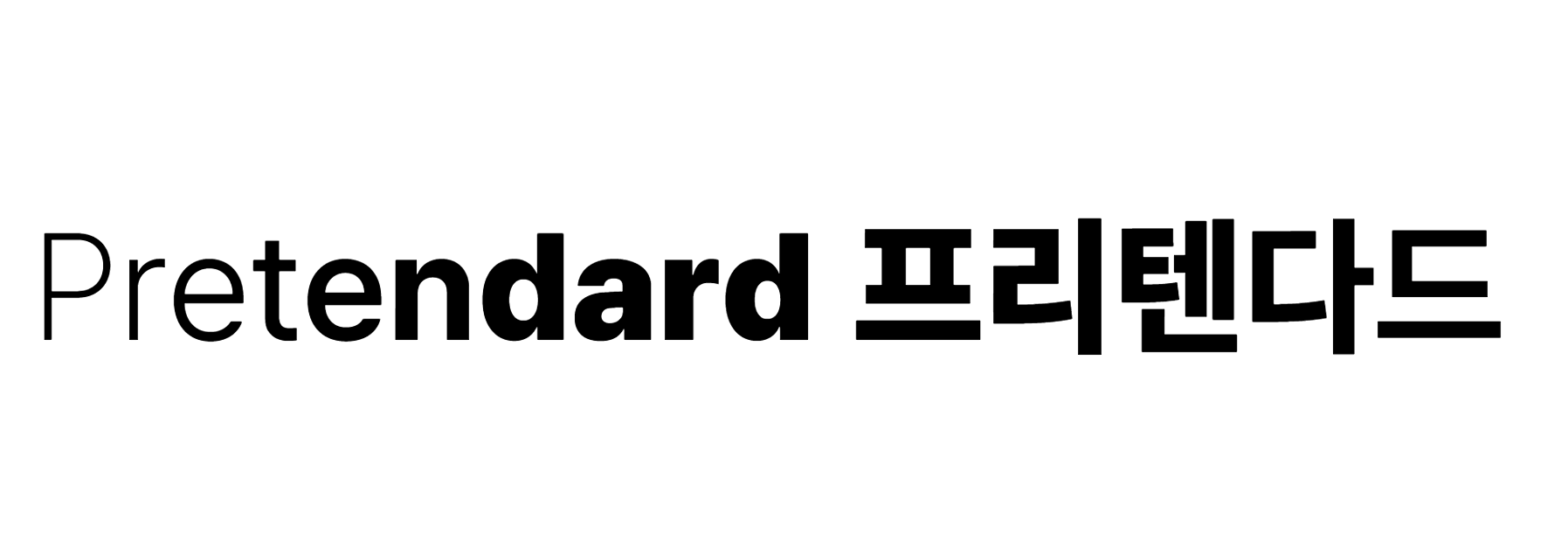
프리텐다드 특징 및 추천 카테고리 (의류/뷰티 상세페이지 본문)
프리텐다드는 최근 웹디자인과 상세페이지 트렌드에서 가장 뜨거운 사랑을 받고 있는 서체입니다. 자간과 행간의 균형감이 매우 뛰어나 의류나 뷰티 상세페이지의 상세 스펙 설명, 브랜드 가치관 전달 등 텍스트 양이 많은 본문 영역에 가장 강력하게 권장되는 폰트입니다.
모바일 화면에서 더욱 빛나는 가독성 장점
스마트스토어 구매 고객의 80% 이상이 모바일 기기로 상품을 조회한다는 사실을 알고 계셨나요? 프리텐다드는 고해상도 디스플레이뿐만 아니라 작은 모바일 화면에서도 글자가 뭉개지지 않고 또렷하게 표현됩니다. 본문 텍스트가 명확하게 읽히기 때문에, 고객 이탈률을 줄이고 체류 시간을 늘리는 데 큰 기여를 합니다.
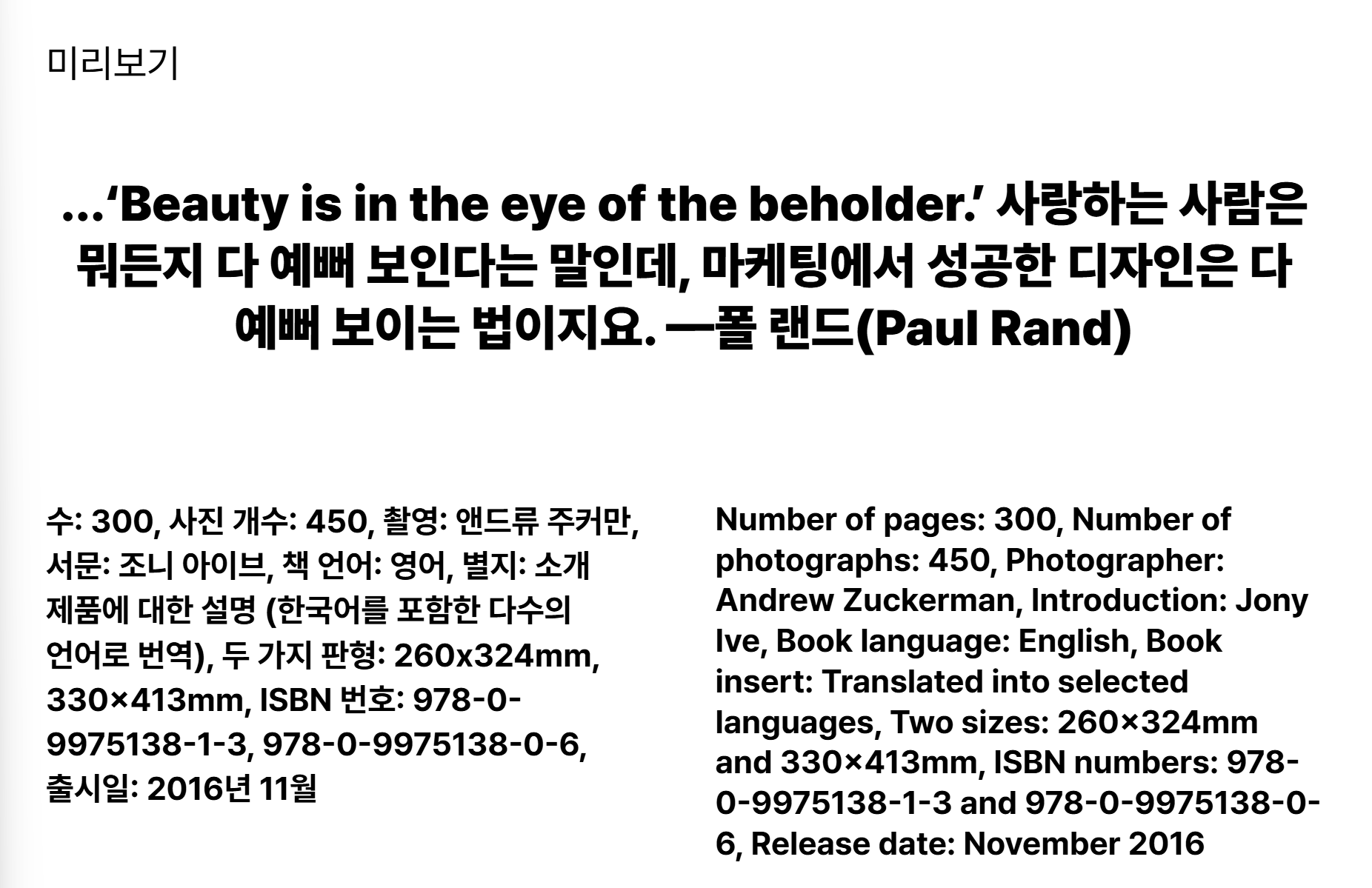
2. 꽉 찬 사각형 구조가 주는 안정감과 모던함 ‘에스코어 드림(S-Core Dream)’
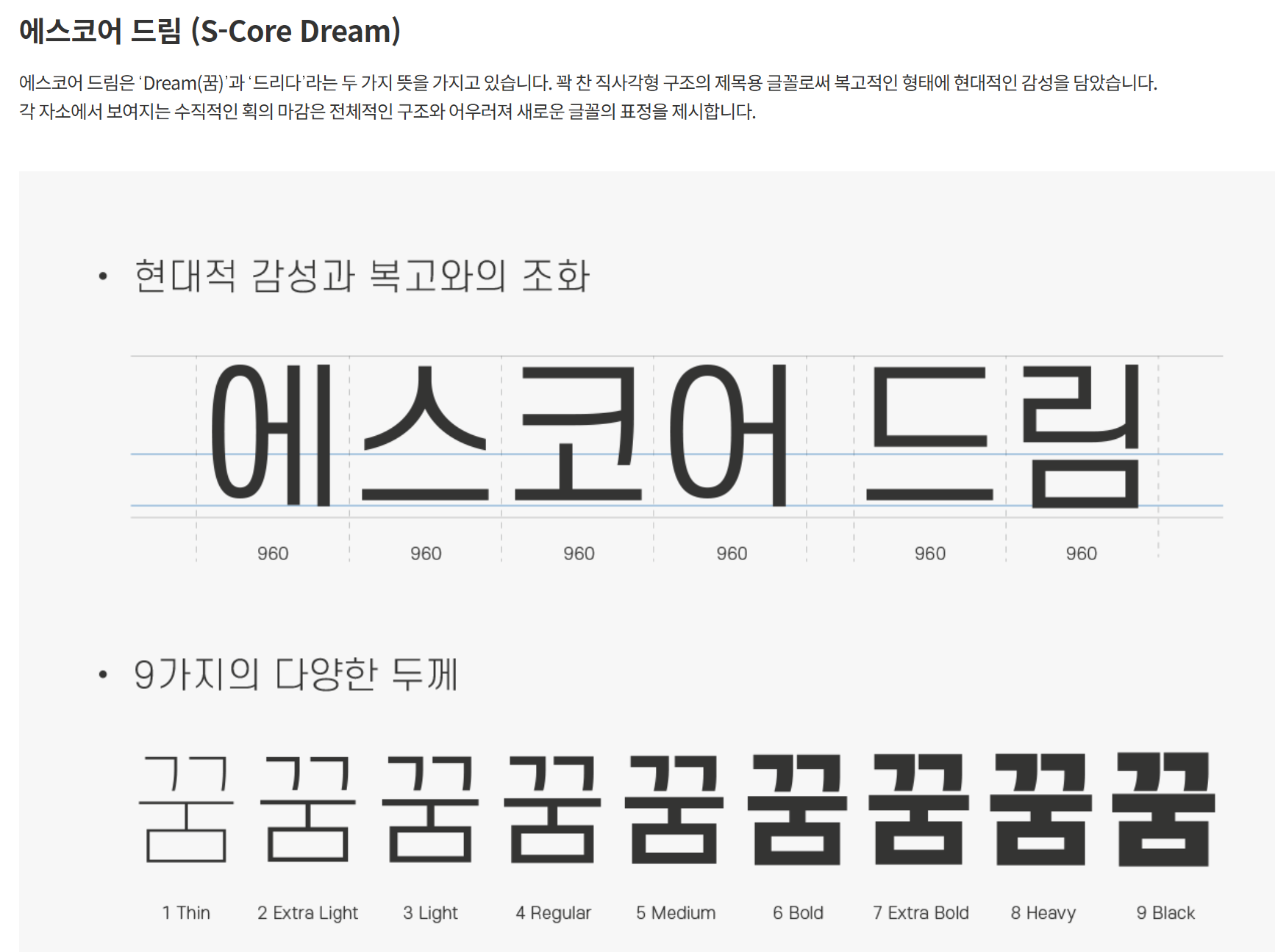
9가지 두께(Thin~Black) 제공으로 높은 활용도
에스코어 드림은 꽉 찬 사각형 구조를 바탕으로 한 서체로, 매우 깔끔하고 신뢰감을 주는 인상을 풍깁니다. 특히 Regular부터 Black까지 총 9가지의 촘촘한 굵기(Weight) 체계를 제공하기 때문에, 하나의 폰트 패밀리만으로 타이틀부터 본문까지 일관성 있는 레이아웃을 완성할 수 있습니다.
깔끔한 화장품 패키지 느낌을 주는 타이틀 적용 팁
에스코어 드림의 매우 얇은 두께(Thin, Light)는 세련되고 차분한 뷰티 브랜드의 로고나 패키지 디자인 같은 느낌을 줍니다. 반대로 굵은 두께(Bold, Black)는 썸네일에서 강력한 타이틀 강조용으로 사용하기에 제격입니다.
3. 아기자기하고 개성 있는 포인트 디자인 ‘카페24 아네모네(Cafe24 Anemone)’
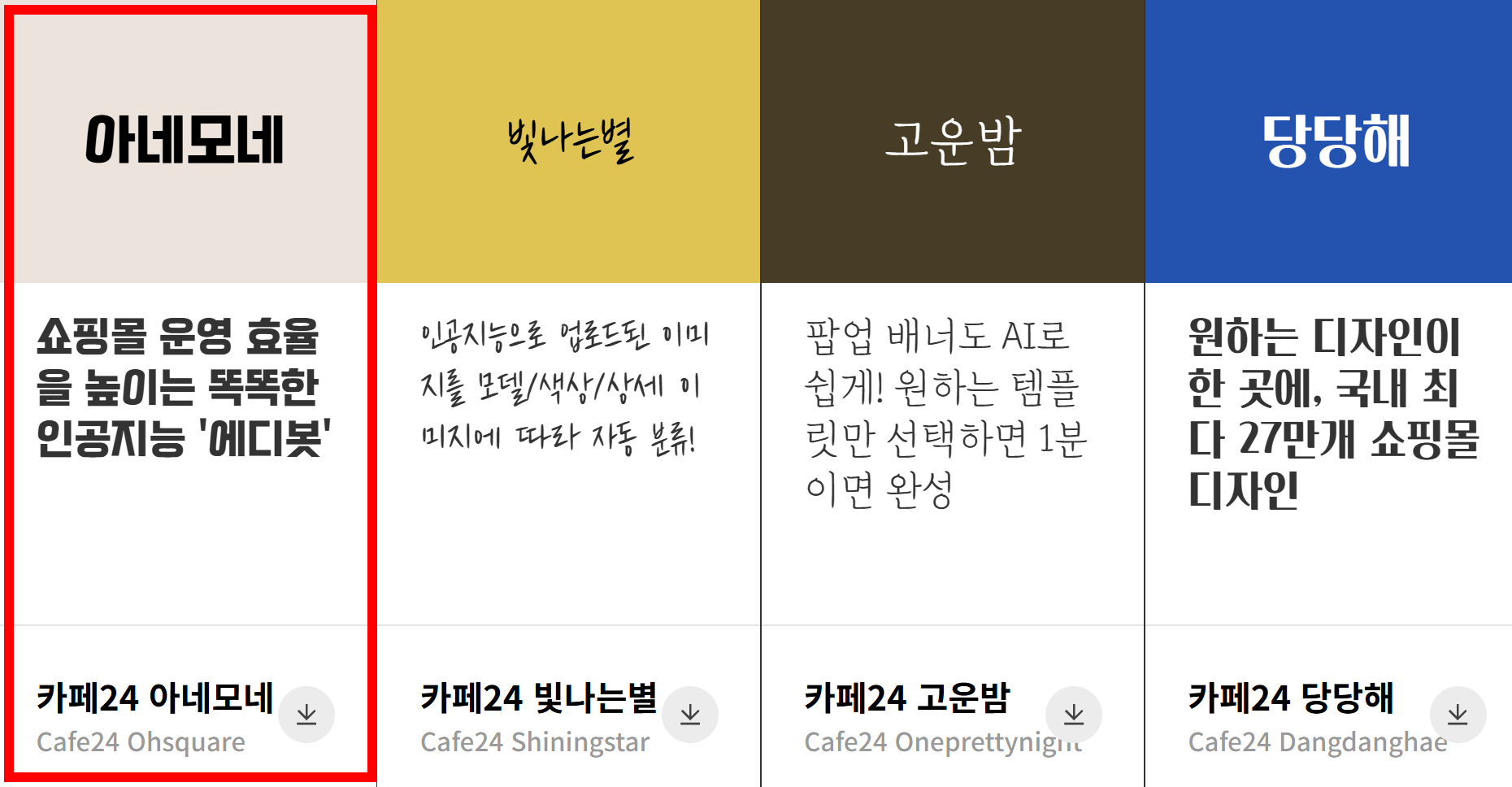
주목도를 높여야 하는 이벤트 배너 및 썸네일 추천
상세페이지 전체를 너무 딱딱한 서체로만 채우면 지루해질 수 있습니다. 이때 '카페24 아네모네'를 활용하면 썸네일이나 이벤트 배너의 주목도를 확 끌어올릴 수 있습니다. 부드러운 곡선과 위트 있는 자모음의 결합이 시선을 단번에 사로잡는 효과를 줍니다.
젊은 타겟층을 저격하는 키치하고 트렌디한 감성 연출법
트렌디한 스트릿 패션 브랜드나 개성 넘치는 인테리어 소품 스토어라면 아네모네 폰트가 지닌 특유의 키치함을 전면에 내세워 보세요. 지나치게 격식을 차리기보다는 친근하면서도 세련된 팝아트 스타일의 브랜드 무드를 구축할 수 있습니다.
4. 따뜻하고 내추럴한 핸드메이드 감성 ‘나눔손글씨 펜’
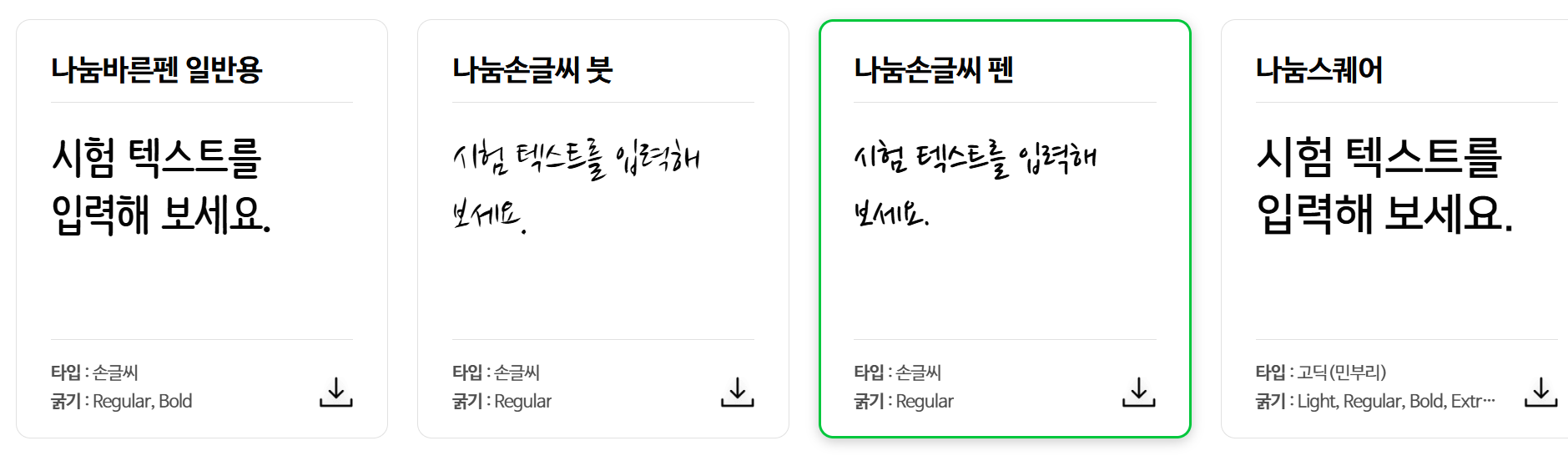
리빙/인테리어 소품 스토어에 어울리는 감성적 터치
자연 친화적인 우드 가구, 친환경 리빙 소품, 핸드메이드 제품 등을 판매한다면 딱딱한 고딕체보다는 따스한 사람의 온기가 느껴지는 손글씨 서체가 좋습니다. 네이버 나눔손글씨 펜체는 자연스러운 필기 감각을 그대로 살려 편안한 느낌을 줍니다.
고객 리뷰 강조 영역이나 손편지 콘셉트에 활용하기
상세페이지 중간에 "대표가 직접 전하는 진심" 영역이나 실제 고객의 리얼 포토 후기 밑에 손글씨 폰트로 한 줄 요약을 적어두면 고객의 신뢰도를 급상승시킬 수 있습니다. 한 끗 차이의 감성이 고객의 마음에 더 가깝게 닿는 순간을 만들어 줍니다.
5. 쇼핑몰 로고와 타이틀에 최적화된 세련미 ‘고도체(Godo)’
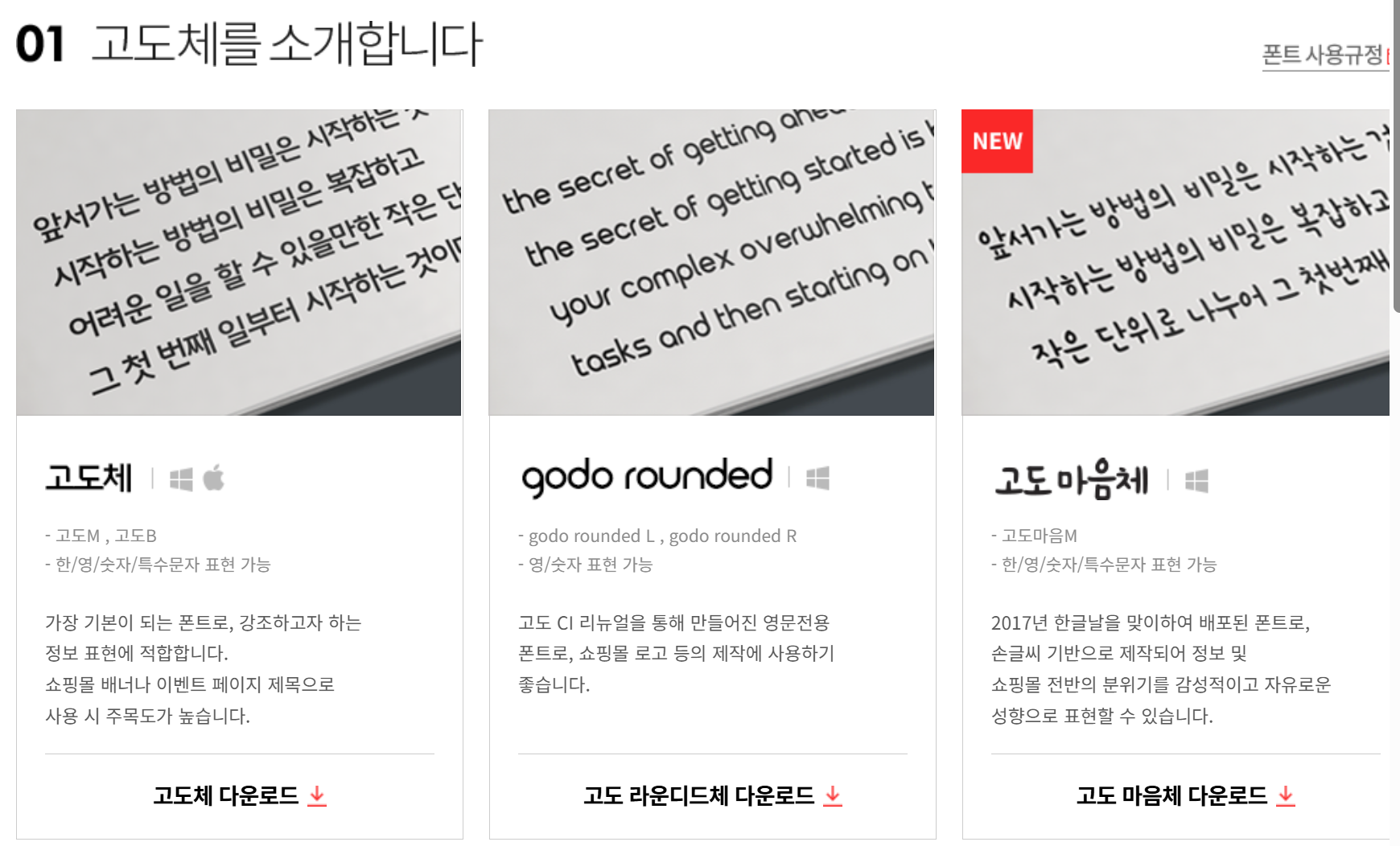
정돈되면서도 개성이 돋보이는 고도 마음체와 고도 라운드체
쇼핑몰 솔루션 NHN고도에서 배포한 '고도체'는 커머스 웹사이트에 최적화되어 제작되었습니다. 곧고 바른 선 속에 둥근 마감 처리가 숨어 있어 지적이면서도 친근한 멋이 돋보입니다.
패션 브랜드의 아이덴티티를 살려주는 영문/국문 조화
고도체는 한글뿐만 아니라 영문 서체의 비주얼 밸런스가 매우 훌륭합니다. 패션 상세페이지 상단에 들어가는 영문 서브 타이틀이나 로고를 만들 때 별도의 영문 폰트를 조합하지 않아도 멋스러운 무드가 자연스럽게 연출됩니다.
6. 테크니컬하면서도 정갈한 느낌 ‘스포카 한 산스(Spoqa Han Sans)’
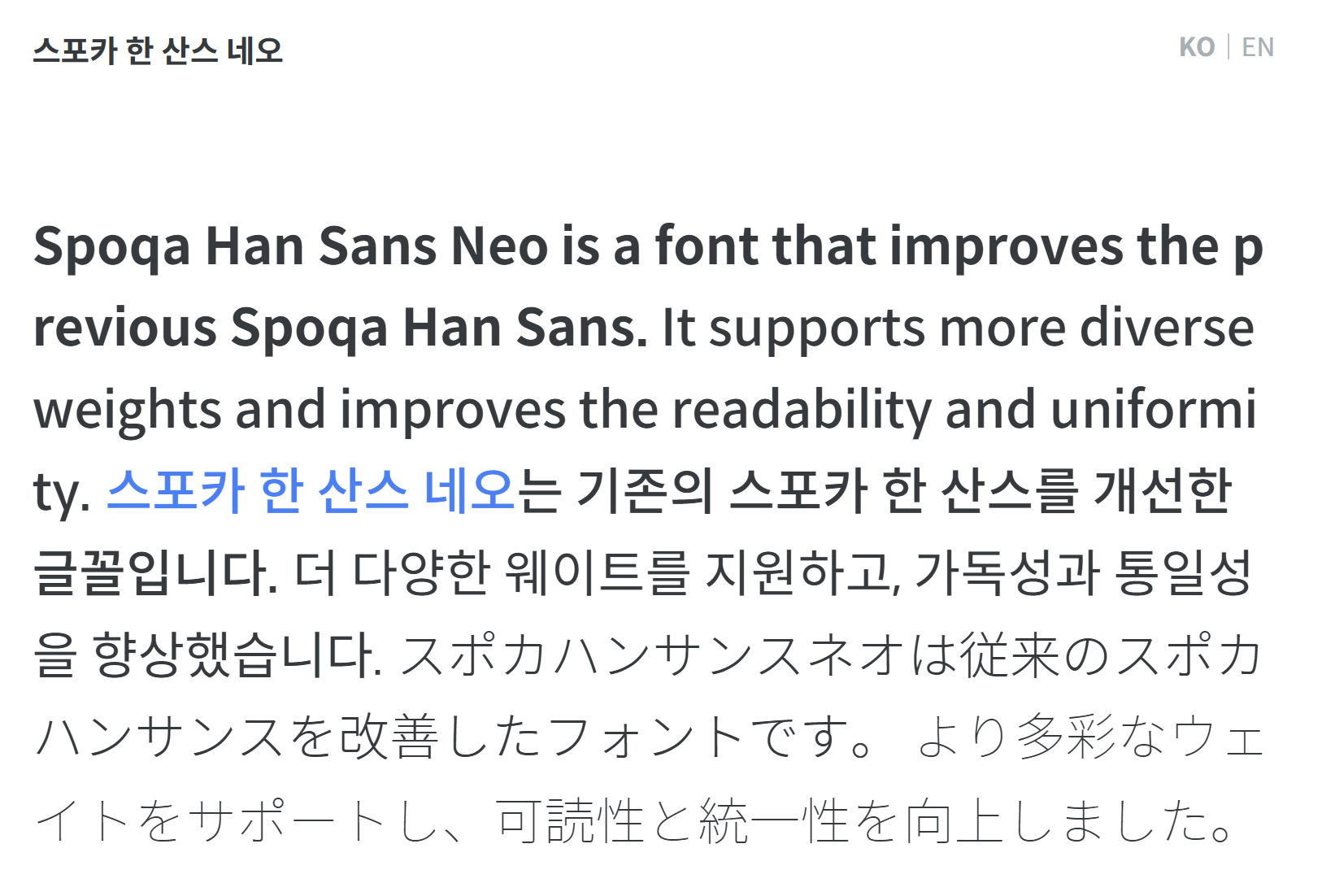
숫자가 많이 들어가는 가격표, 사이즈표에 추천하는 이유
스포카 한 산스는 본래 UI 디자이너들 사이에서 널리 사랑받는 서체입니다. 이 폰트는 한글뿐만 아니라 '숫자'의 자간과 굵기 밸런스가 최고 수준으로 튜닝되어 있습니다.
- 추천 활용 포인트: 상세페이지 하단의 제품 규격표, 실측 사이즈표, 수량 대비 가격 할인표 등에 사용하면 숫자 가독성이 극대화되어 정보 전달이 명확해집니다.
글로벌 웹폰트 표준에 맞춘 깨짐 없는 가독성
웹 브라우저의 종류나 안드로이드, 아이폰 등 운영체제에 상관없이 텍스트 깨짐 현상이 전혀 발생하지 않는 정교함을 자랑합니다. 깔끔하고 정확한 정보 전달이 필수적인 전자기기, 정밀 가구, 건강보조식품 등의 상세페이지 디자인에 적극 추천합니다.
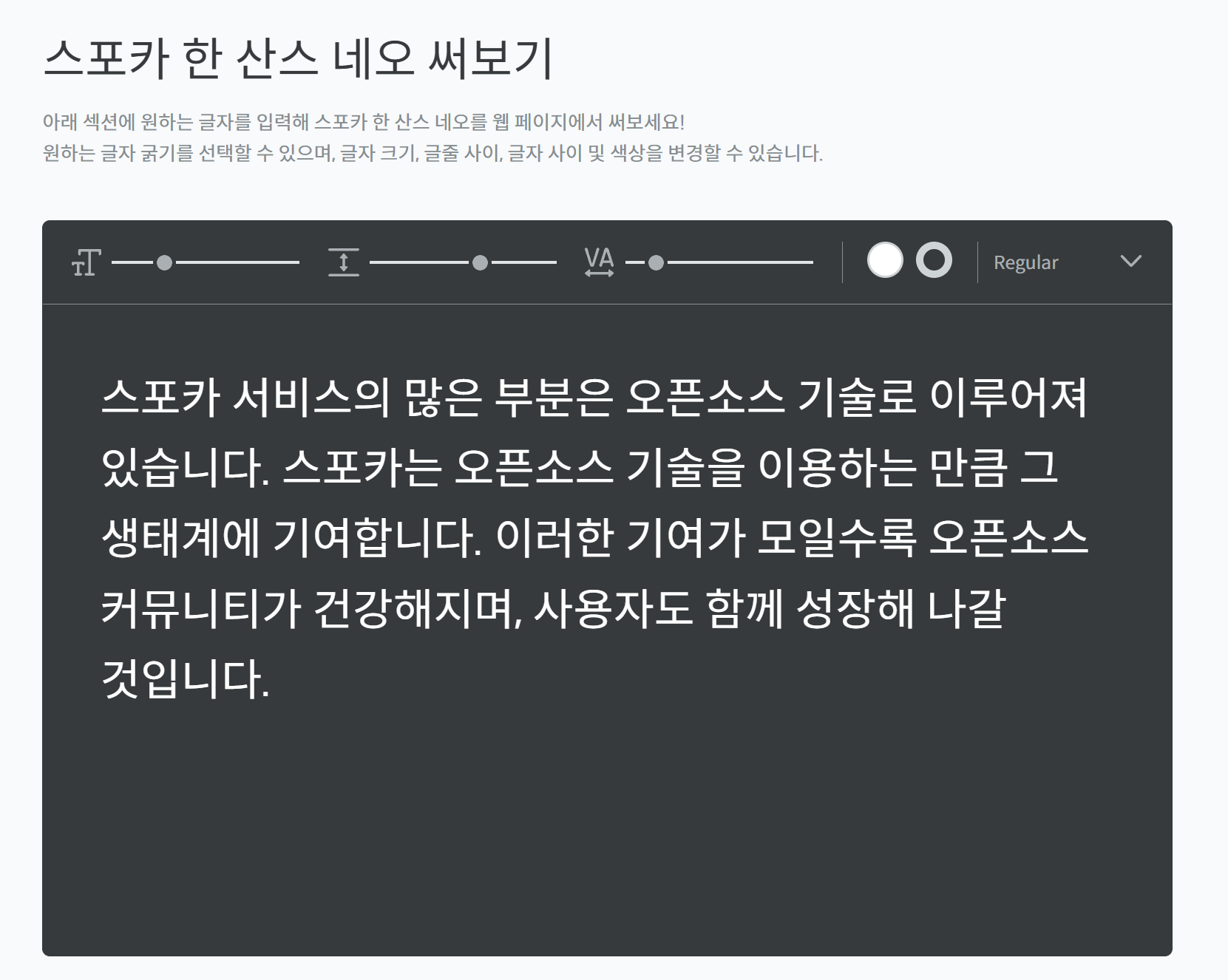
7. 차분하고 고급스러운 잡지 레이아웃 감성 ‘리디바탕’
명조 계열 폰트가 주는 클래식하고 우아한 분위기
모던한 고딕체 일색인 시장에서 차별화를 두고 싶다면 품격 있는 명조체인 '리디바탕'을 눈여겨보세요. 전자책 플랫폼 리디에서 화면 가독성을 위해 극도로 공들여 만든 명조 서체로, 일반적인 서체에 비해 부드러우면서도 묵직한 힘을 지니고 있습니다.
뷰티 브랜드 스토리나 브랜드 철학 소개 영역에 최적화
고급 유기농 에센스, 프리미엄 디퓨저 등 하이엔드 무드를 지향하는 브랜드라면 리디바탕 폰트를 크게 배치해 보세요. 고급 인쇄 잡지(Magazine)의 한 페이지를 읽는 듯한 클래식하고 고혹적인 레이아웃을 아주 간편하게 완성할 수 있습니다.